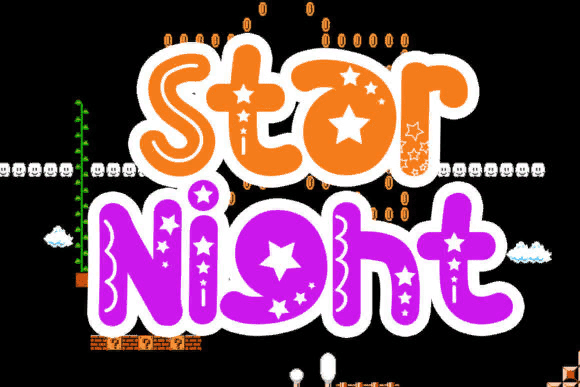
Название: Star Night Font
Star Night - это веселый и забавный шрифт.
Он воплощает игривость и подлинность и идеально подходит для любого детского мероприятия или школьного проекта.